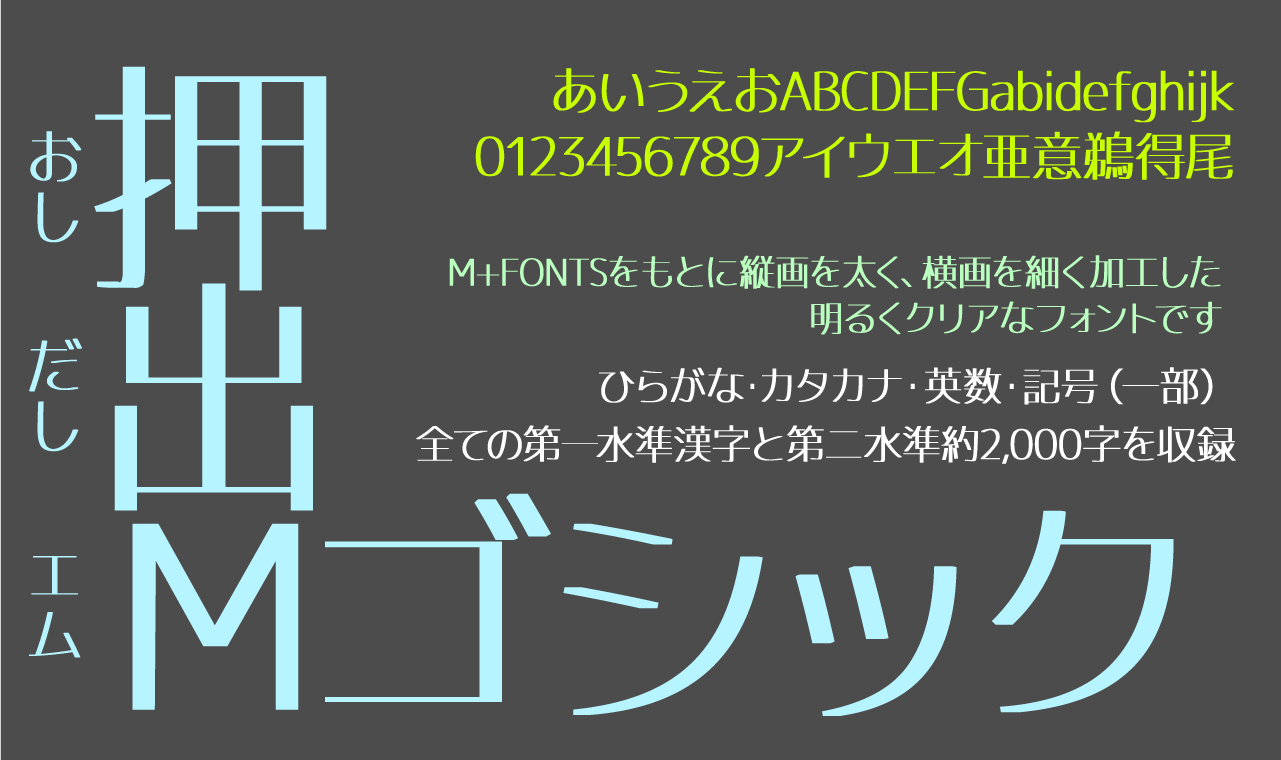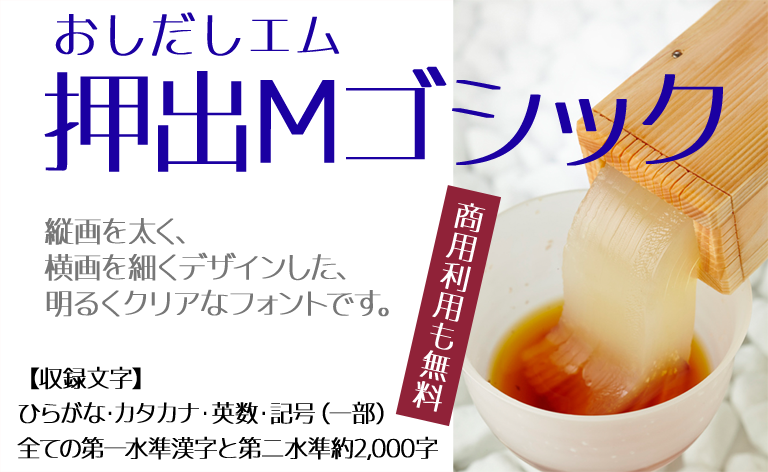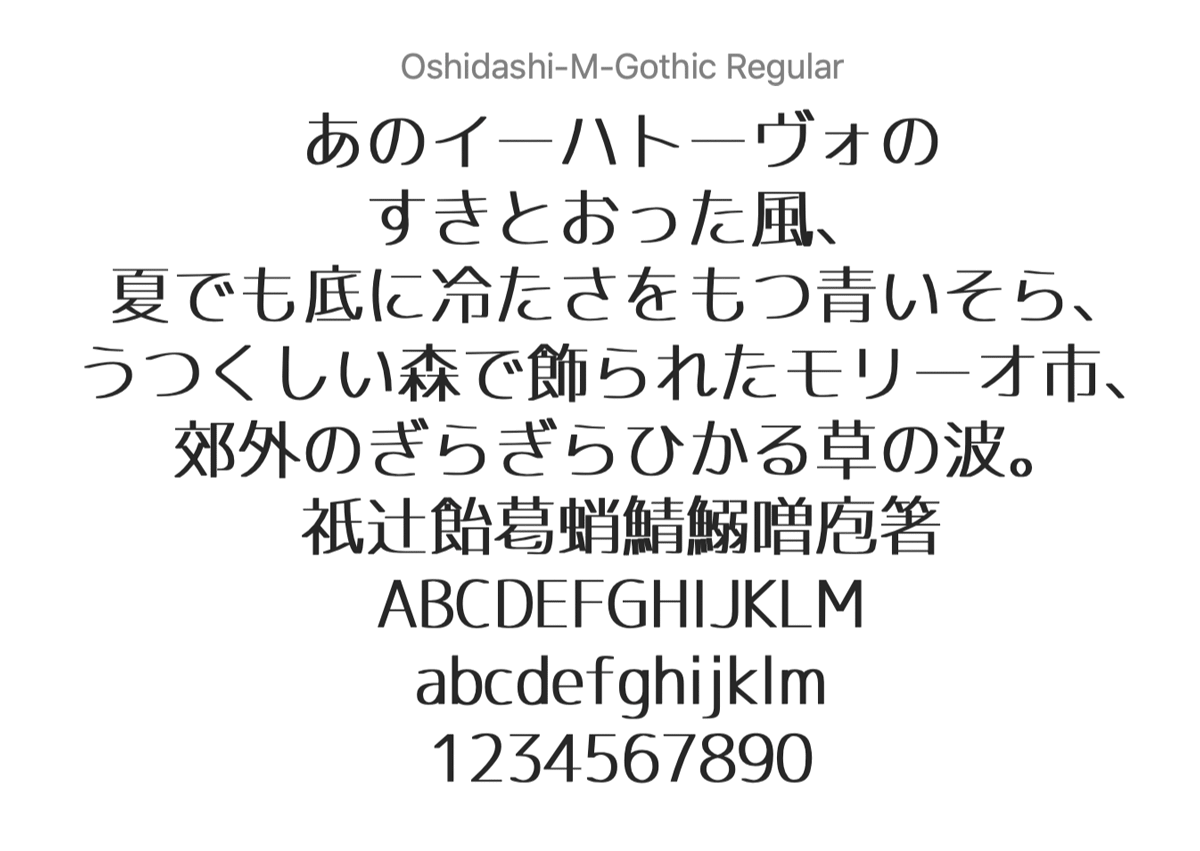
押出Mゴシック
押出Mゴシック(Oshidashi M Gothic)是一款由日本字体设计师たぬき侍制作的日系无衬线字体。字体以旧版 M+ FONTS 中的 M+1c Thin 为基础进行加工,通过调整笔画粗细关系,让纵画更加厚实、横画保持纤细,并融入少量类似明朝体的笔画变化,形成清晰、明亮而富有现代感的文字风格。
从整体字形来看,押出Mゴシック并没有采用传统黑体均匀一致的笔画处理,而是刻意强化了纵向笔画的存在感。粗细对比让文字拥有更加鲜明的结构,同时保持较为轻盈的视觉效果。部分转折与端部带有细微的衬线感,使字体在简洁的基础上增加了一些精致的细节。
在日文假名的表现上,押出Mゴシック同样延续了纤细、清爽的设计思路。平假名与片假名的线条舒展,字面结构较为开阔,与英文、数字组合时能够保持自然的节奏感。英文字符采用简洁的无衬线结构,数字和部分符号也具有较明显的横竖粗细对比,适合用于标题、短句以及具有视觉设计感的排版。
字符收录方面,押出Mゴシック支持平假名、片假名、英数字以及部分标点和符号,并收录全部第一水准汉字共2965字,同时包含部分第二水准汉字2155字以及9个IBM扩展汉字,能够满足一定程度的日文及中日混排设计需求。
总体而言,押出Mゴシック是一款建立在开源字体基础上的特色改造字体。通过将纵画加粗、横画细化,并加入轻微的明朝体式变化,它在传统日系无衬线字体的基础上形成了更加鲜明的粗细对比,既保留了阅读上的清晰度,又具有一定的设计感。对于喜欢日系简约排版、细线字体以及独特笔画比例的设计师来说,这款字体可以作为标题与视觉设计中的一个不错选择。